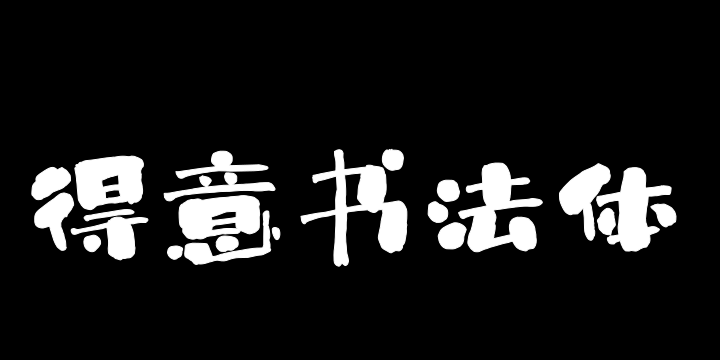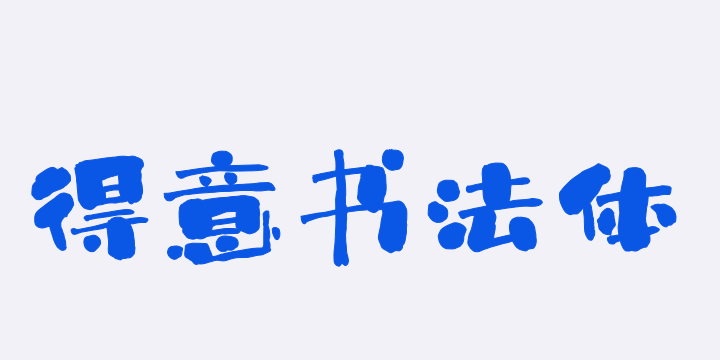
上首得意书法体 By 上首造字 商用字体
字体全名: 上首得意书法体
铸字厂: 上首造字
设计师: 胡博剑
字体简介: 上首得意书法体,简体中文约6763字,笔画起笔处形如蚕头,圆润且藏锋;收笔处如燕尾,呈波磔之态,有明显的捺脚,通过细节创新提升艺术感染力。书写时通过提按来表现笔画粗细变化和节奏感,形成独特的韵律美。